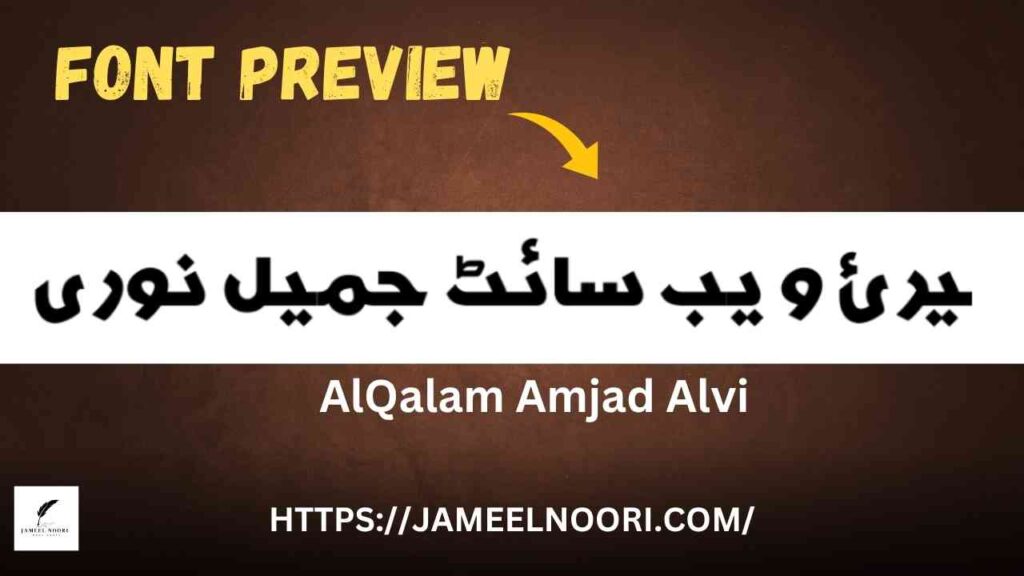
Introduction – urdu font AlQalam Amjad Alvi Kya Hai?
AlQalam Amjad Alvi Urdu Font ek khubsurat aur high-quality Nastaleeq style font hai jo Urdu likhne ke liye khas tor par tayar kiya gaya hai.. Is font ka design readable, elegant, aur modern appearance ka behtareen mix hai.. Yeh font Urdu designers, calligraphers, aur Islamic publishers ke liye ek pasandeeda choice ban chuka hai..
Urdu Font AlQalam Amjad Alvi Ke Features
- ✅ Nastaleeq style Urdu writing ka behtareen example
- ✅ Professional aur Islamic content ke liye recommended
AlQalam Amjad Alvi Font Ka Use Kahan Hota Hai?
Yeh Urdu font commonly use hota hai:
- 📰 Urdu Newspapers aur magazines mein
- 🖋️ Urdu Poetry aur Quotes design mein
- 📖 Islamic aur Urdu books publishing mein
- 🎨 Graphic design aur calligraphy projects mein
- 🎬 YouTube thumbnails aur titles ke liye
❓ Is font ka style kis tarah ka hai?
✔️ Iska style elegant aur professional Nastaleeq Urdu ka hai – suitable for all kinds of content..
Conclusion – Urdu Ka Khubsurat Izhar
Agar aap Urdu likhne ka shauq rakhte hain ya kisi professional ya Islamic publishing project mein kaam kar rahe hain to AlQalam Amjad Alvi Urdu Font aap ke liye behtareen tool hai.. Iska graceful aur readable style aapke content ko aur bhi attractive banata hai.